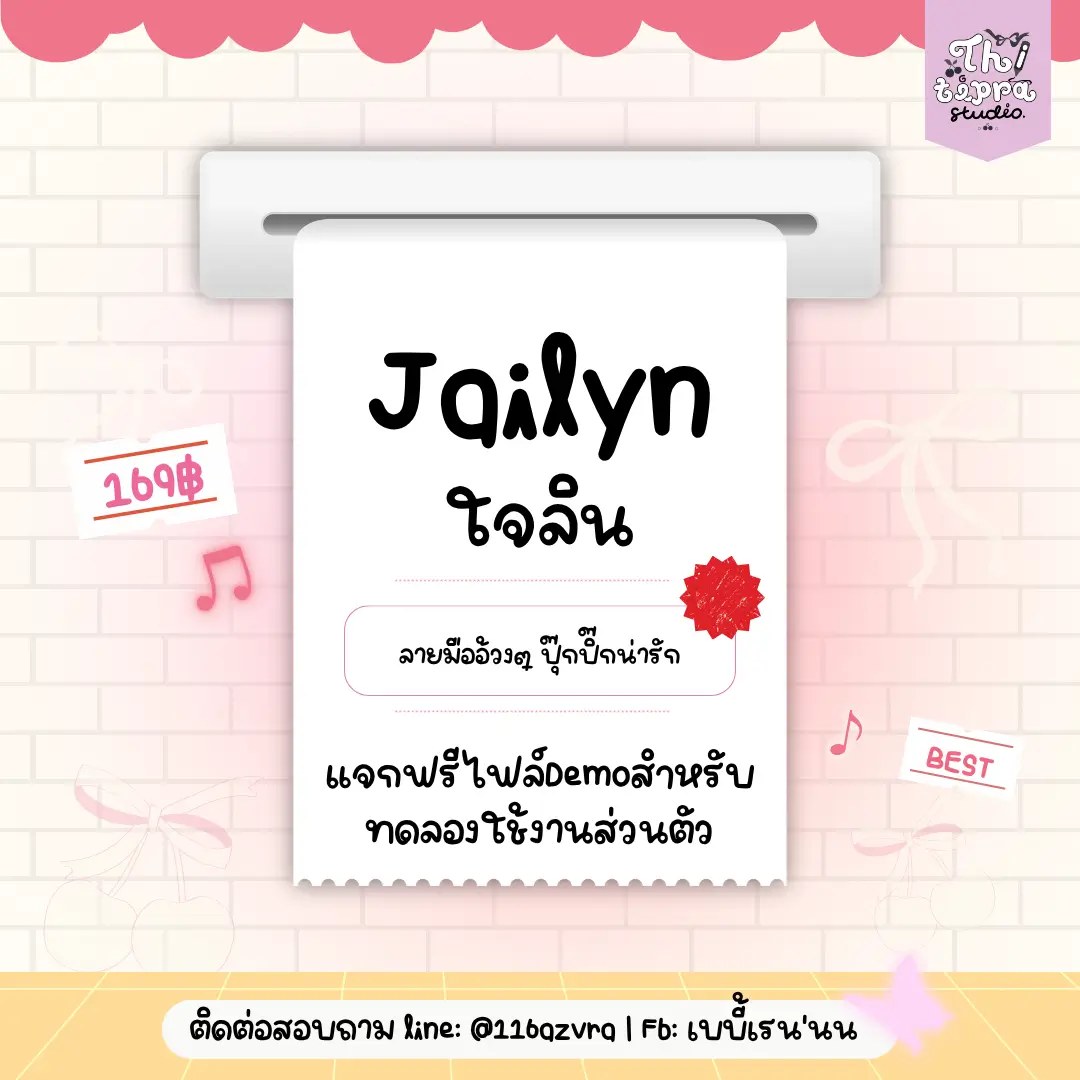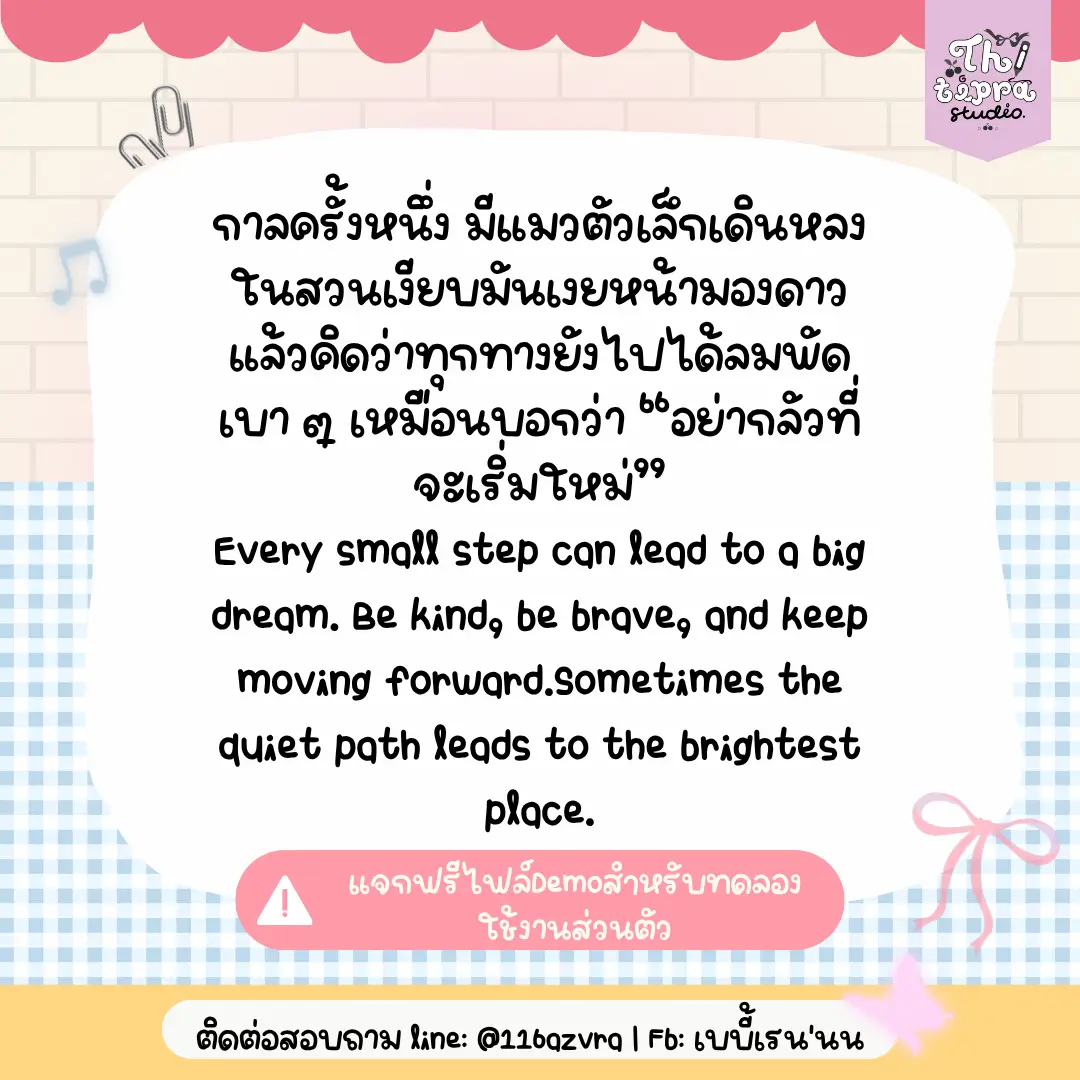
ใจลินฟอนต์ (PRHJailyn) – THITIPRASTUDIO : ฟอนต์เนื้อหาอ้วงๆ ปุ๊กปิ๊ก น่ารัก แต่งกับอะไรก็น่ารักไปหมด
- เหมาะสำหรับ เช่น งานส่งครู ไดอารี่ แพลนเนอร์ สรุป แต่งรูปส่วนตัว ฯลฯ
- ตัวอักษรครบ ปรับสระเรียบร้อย พร้อมใช้งาน